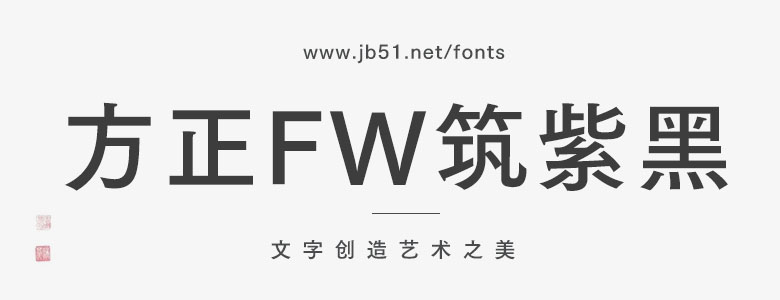
筑紫黑家族在設(shè)計上一直基于與2003年發(fā)布的筑紫宋體家族一致這一原則進行新的開發(fā)。使用范圍廣,包括書籍、雜志、目錄、廣告單等,重視文字的質(zhì)感,保證要求品位時也可以滿足要求。這是由八個字重組成的黑體家族系列,正文、解說詞、小標(biāo)題、大標(biāo)題均設(shè)計為最佳表達方式。
筑紫黑體的書法風(fēng)格將現(xiàn)代的鮮明感、潔凈的堅硬感、經(jīng)典的趣味以及柔和融為一體,既正統(tǒng)又給人新鮮感。在重視現(xiàn)代字體設(shè)計的主流“均質(zhì)性和均勻性”的同時,又不忘記“文字是邊用手寫邊設(shè)計形成的”這一點,與筑紫宋體同樣地使“寫”這一手的動作坦率地表現(xiàn)在文字中。能看出“寫”這一動作,是基本字體的使命“鮮明地突出文章的含義”這一表現(xiàn)力的源泉。在建立、使用和閱讀字體的各個行為中重新驗證了可以表現(xiàn)現(xiàn)代世界的黑體的使命和作用,這是設(shè)計的根本,筑紫黑體就是在對這個根本的重新審視中產(chǎn)生的。